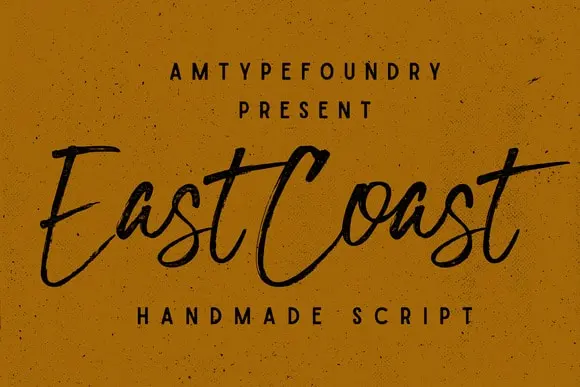
East Coast Script Font – Download Grátis
East Coast Script Font é uma fonte que retrata a autêntica elegância dos textos escritos à mão no leste do país. Desenvolvida pelo designer 178-MC, essa fonte se inspira na mistura perfeita de traços humanos com o suavidade da caneta. Esta é uma escolha ideal para designers que buscam um estilo natural e sofisticado, pois a East Coast Script Font transmite a sensação de letras escritas por pessoas em vez de computadores. Ela oferece uma abordagem versátil à criação de design gráfico, permitindo que você personalize suas obras com o charme único dessa fonte. Não hesite em adicionar essa elegância ao seu próximo projeto visual.